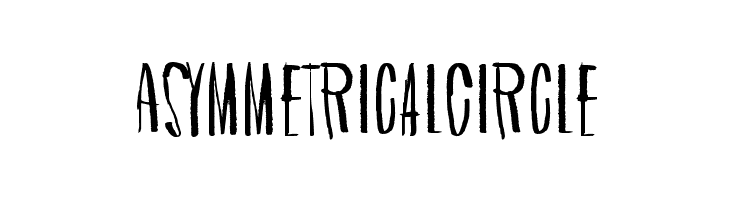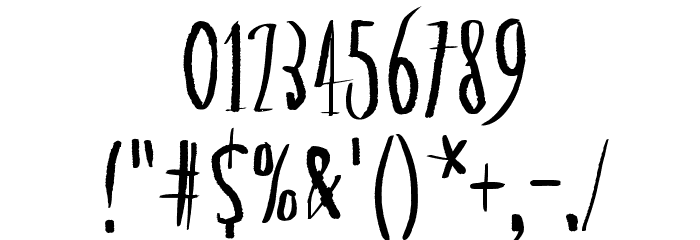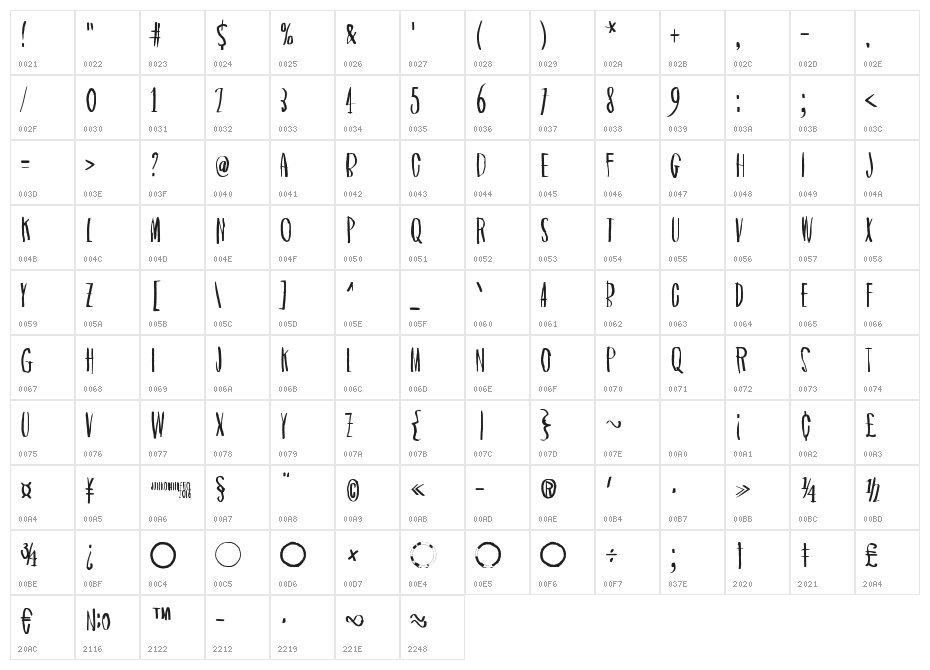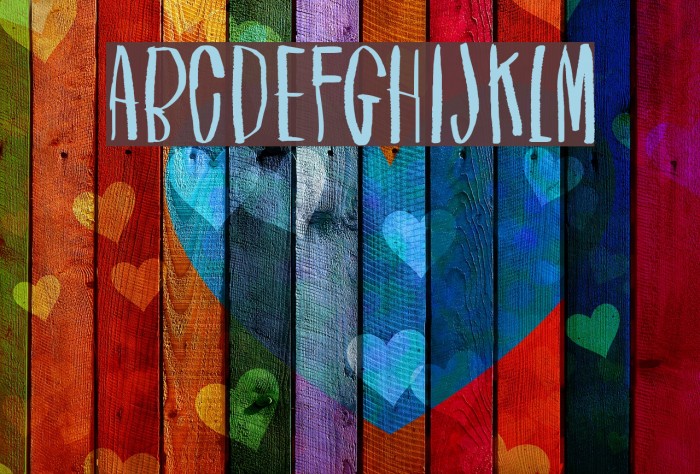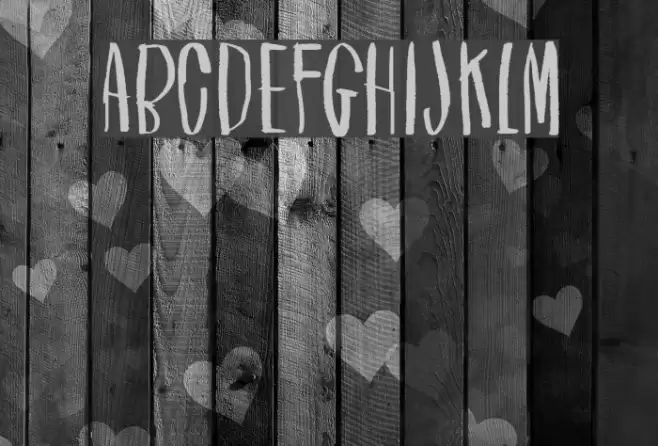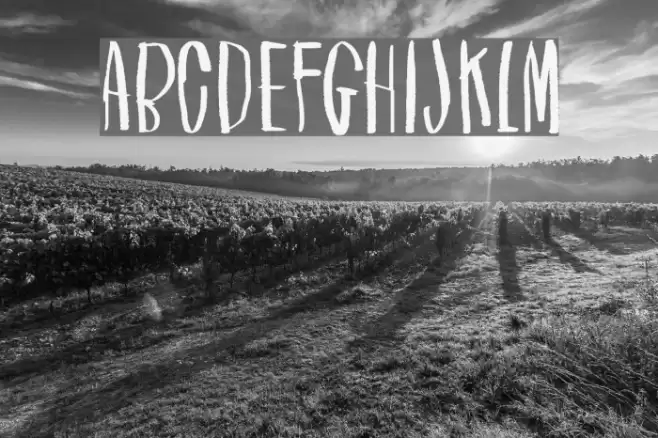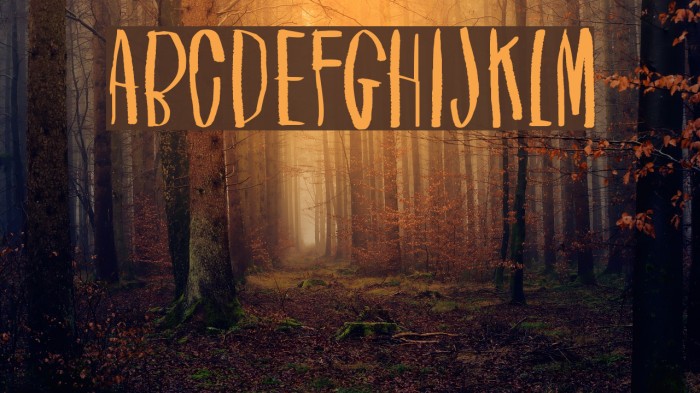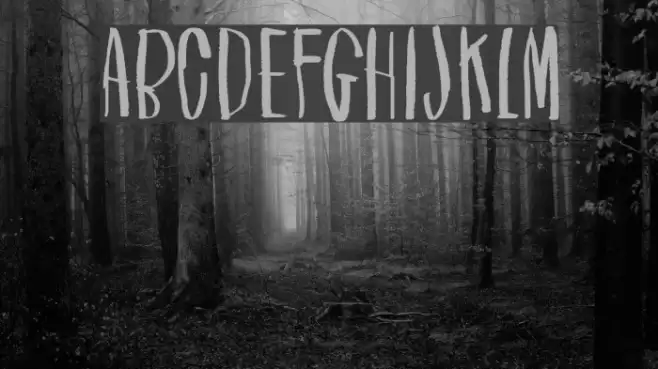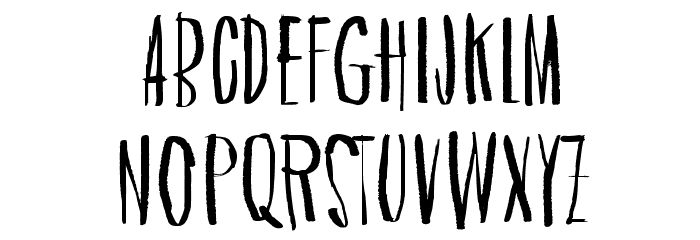
Asymmetrical Circle Font
| Caso de uso | Logos, Headlines, Creative projects |
| Proyectos propuestos | Ideal for artistic projects, branding, posters, and invitations where a personal and creative touch is desired. |